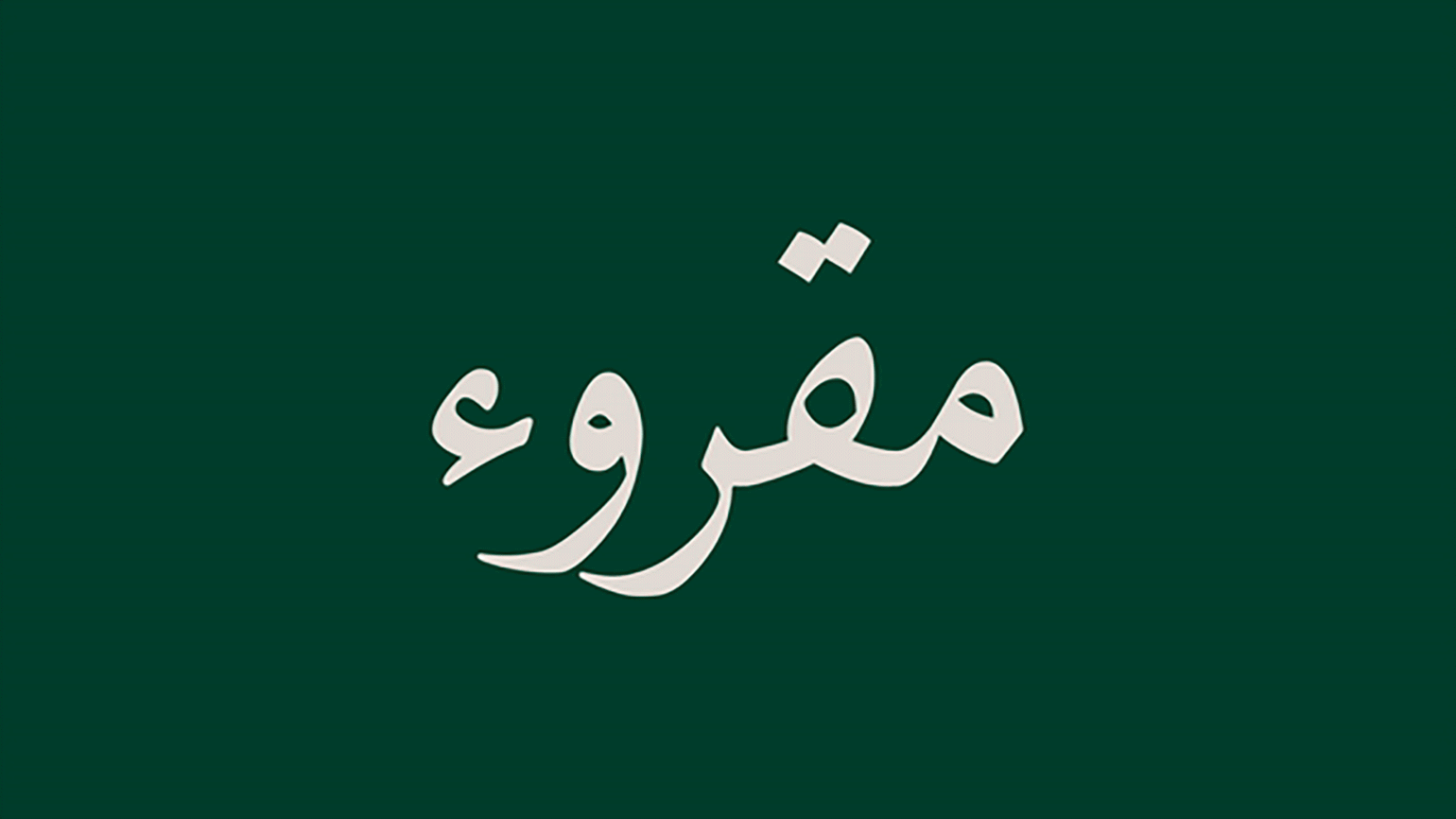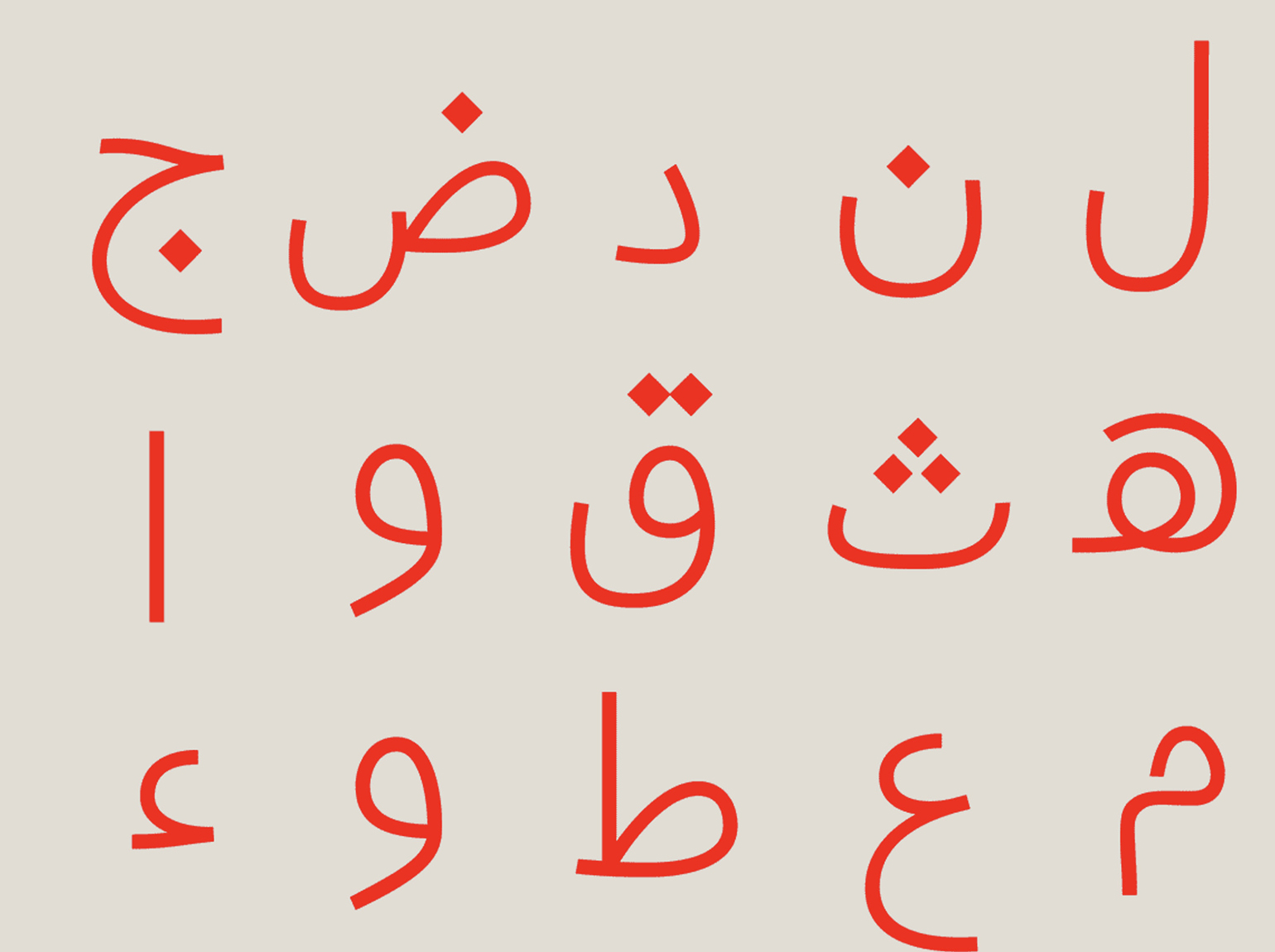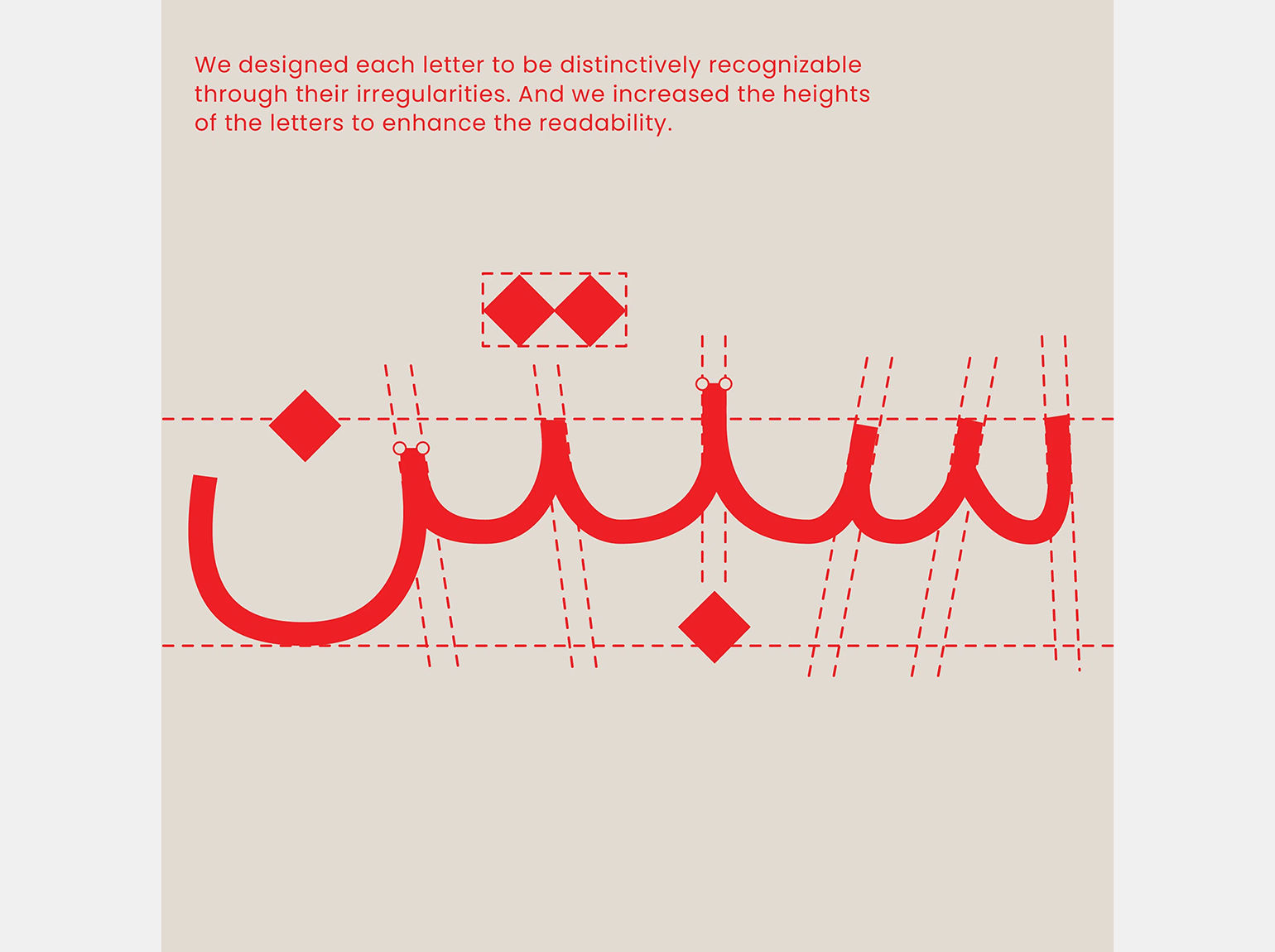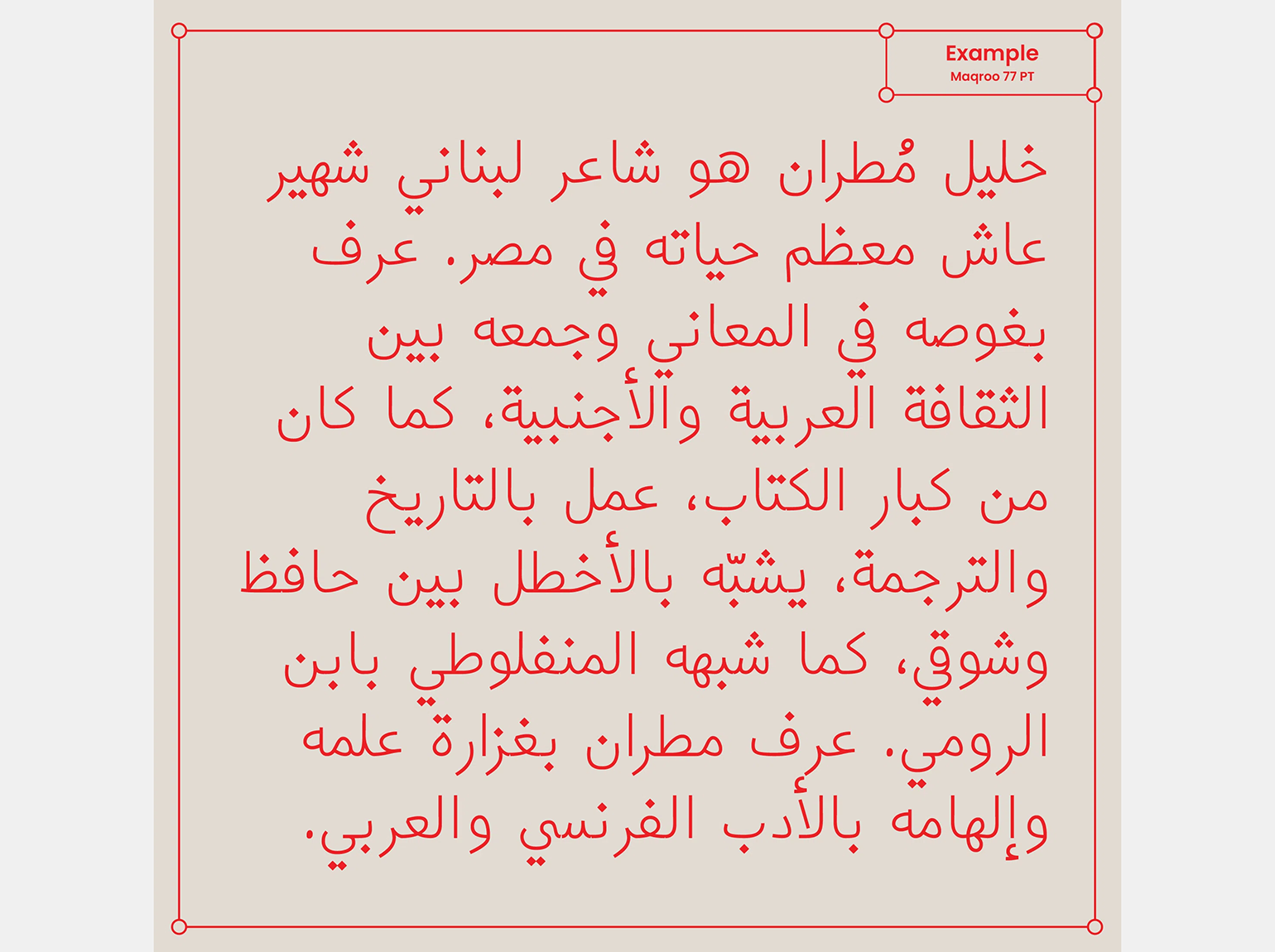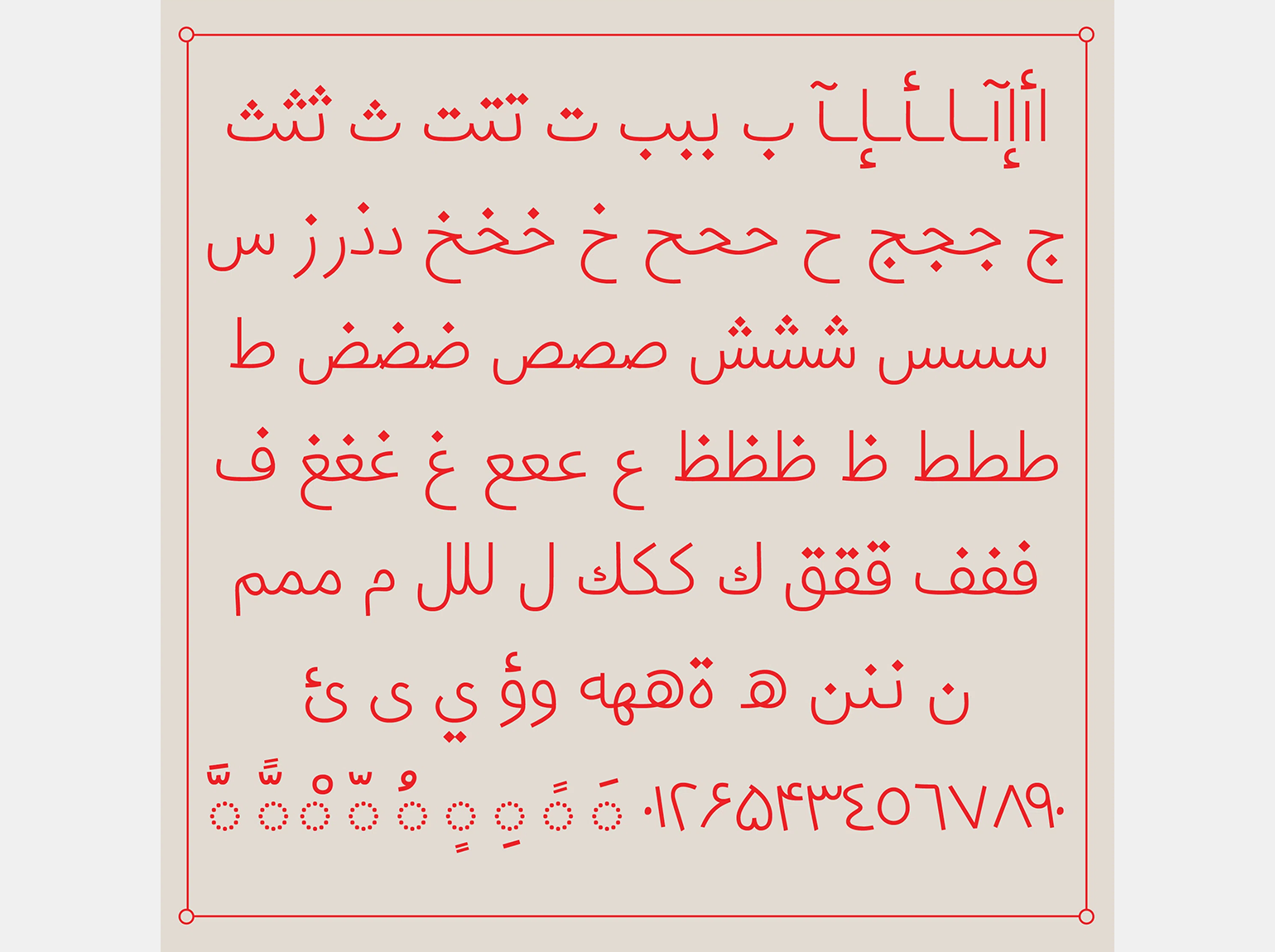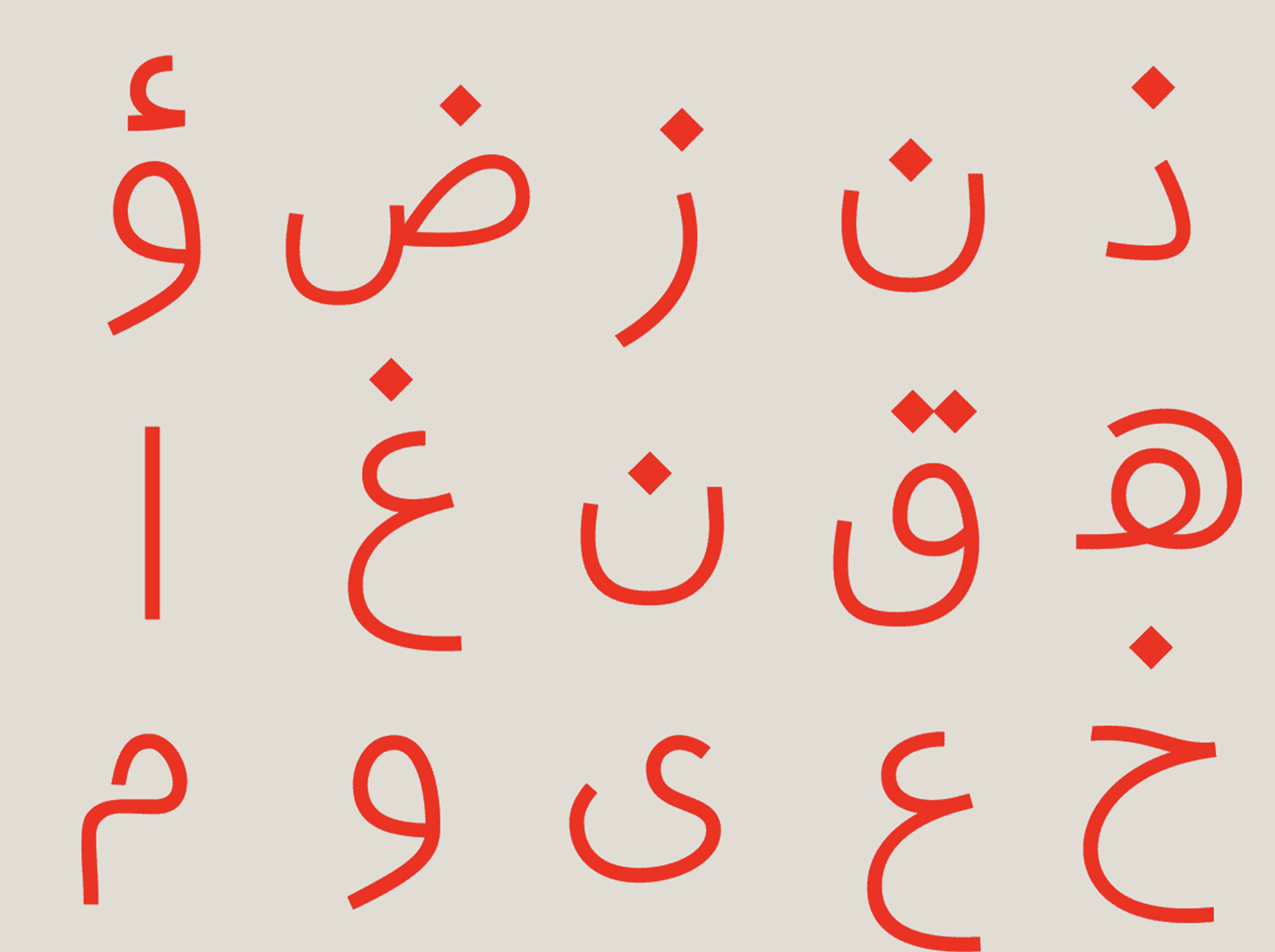
В Омане создали арабский шрифт для читателей с дислексией
Он называется Maqroo, что переводится как «читаемый».
Его разработало агентство Leo Burnett Dubai в партнёрстве с телекоммуникационной сетью Omantel. Арабский язык является одним из самых сложных, особенно для людей, страдающих дислексией. По словам арт-директора агентства Абдо Мохамеда, они не смогли найти ни одного широко используемого арабского шрифта для таких людей. При этом в странах MENA (это географический регион, объединяющий страны Магриба и Ближнего Востока) трудности с обучением испытывают больше 8,4 миллиона человек.
Предварительные исследования шрифта проводились в тесном сотрудничестве с людьми, страдающими дислексией. Это помогло команде проанализировать и понять множество арабских шрифтов — участников исследования просили читать, рисовать и зарисовывать то, что они воспринимают при чтении различных шрифтов.
Кроме того, команда оценивала их уровень стресса — так определили характеристики шрифтов, которые помогают и которые этого не делают. На этом совместная работа не закончилась, процесс был непрерывным: каждый из черновиков Maqroo проверялся добровольцами на удобочитаемость.
Одним из самых интересных открытий стало то, что для многих людей с дислексией единообразие лигатур, засечек и других аспектов шрифтов на самом деле не способствует удобству чтения.
Арабские буквы имеют во многом одинаковую структуру и внутренние пространства, и это один из факторов, делающих их трудноразличимыми. Поэтому команда поняла, что, например, делая внутренние пространства разного размера, можно добиться того, что глифы будет легче определять.
Команда также использовала другие отличительные аспекты арабской типографики, такие как нукты (точки) и ташкили (знаки), сделав их больше и добавив неровности в форме и размере. Это тоже делало их более различимыми. Каждый глиф таким образом стал узнаваемым благодаря своим неровностям, сообщает издание It’s Nice That.
Абдо продемонстрировал, как это работает, в серии видеороликов. В одном из них шрифт показан без различных внутренних пространств, а затем с различными внутренними пространствами. Хотя Абдо понимает, что некоторые могут воспринять эти изменения как «непоследовательный дизайн», он осознаёт, насколько такие мелкие детали могут оказать влияние на людей с дислексией.
Теперь Omantel планирует использовать Maqroo на всех своих цифровых платформах, а также в печатных материалах, включая его во все точки контакта с клиентами. В будущем компания также хотела бы создать шрифт с открытым исходным кодом, чтобы им могли пользоваться другие бренды и члены сообщества арабских дизайнеров, чтобы привнести больше инклюзивности в цифровые коммуникации, говорит Абдо.
В долгосрочной перспективе планируется использовать Maqroo в учебных заведениях, чтобы обеспечить следующее поколение студентов материалом, отвечающим их потребностям.